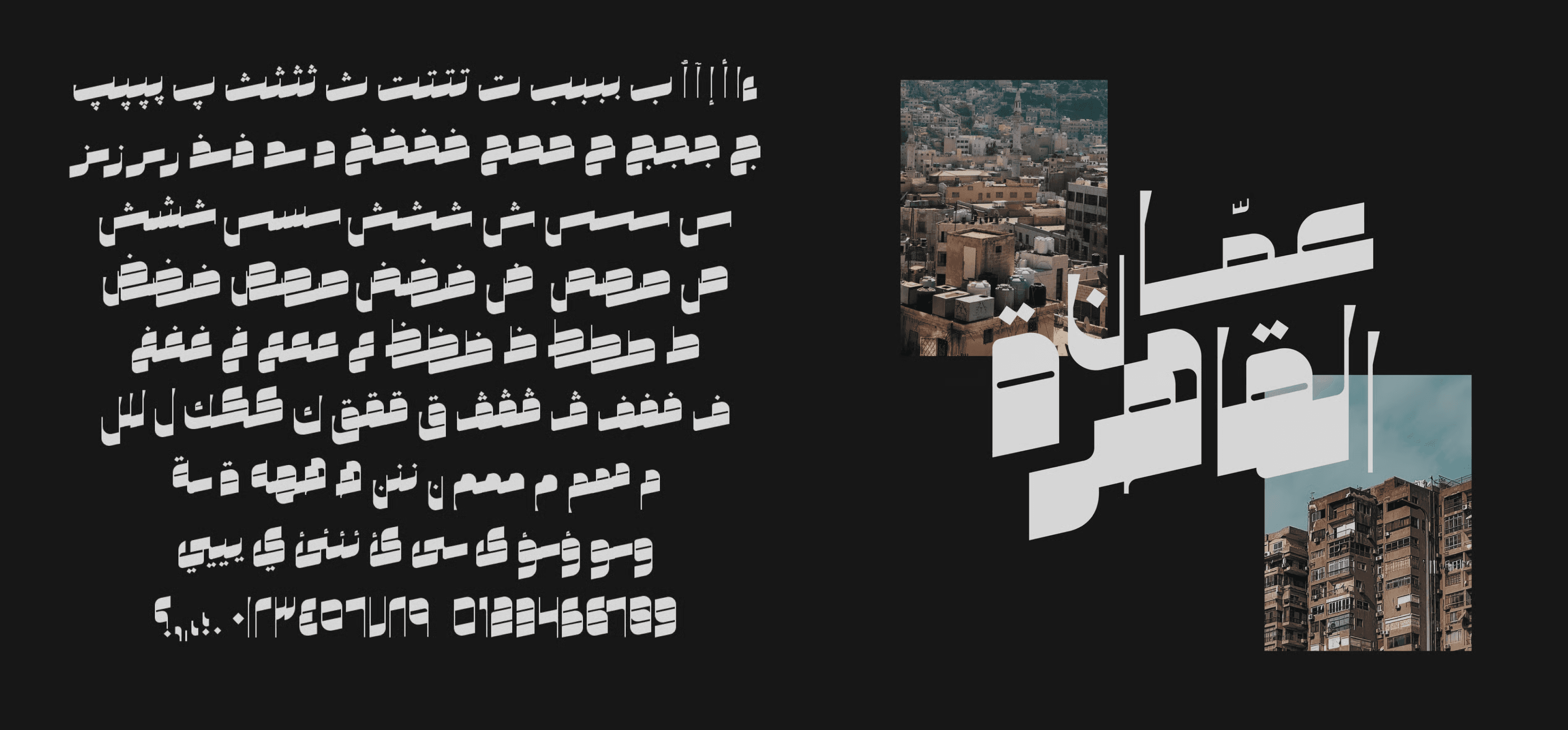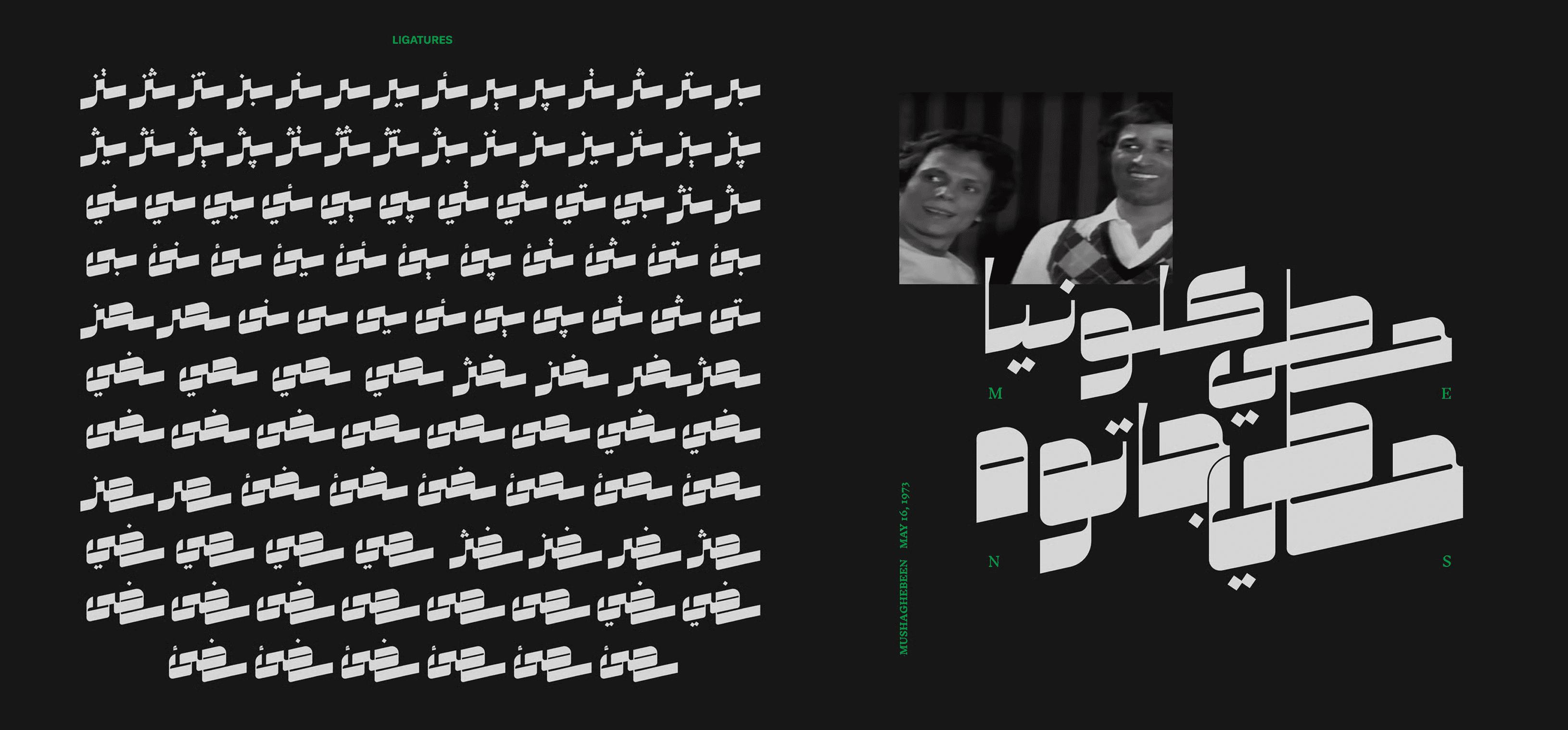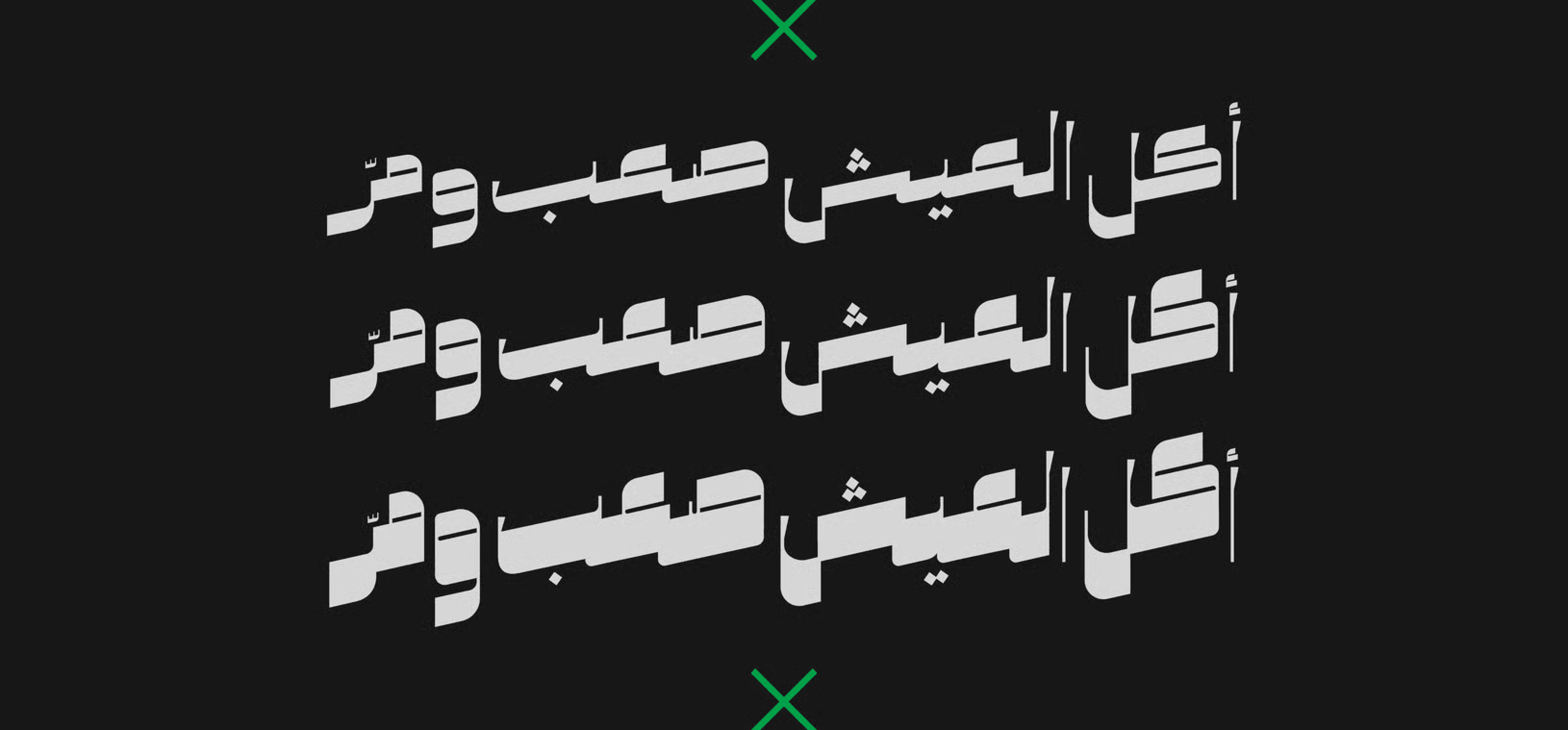
هو خط عربي ديناميكي مستمد من مزيج من خطي الرقعة والنستعليق، يتميز بخط أساس مائل ولمسة هندسية عصرية، ويُظهر تباينًا قويًا بين السماكات الرفيعة والسميكة للخطوط، مما يمنحه انطباعًا يجمع بين الطابع الرجعي المستقبلي والجدية الخطية العربية. ويأتي مع خمس مجموعات أسلوبية تتيح له تنوعًا واسعًا في الإمكانيات الطباعية."